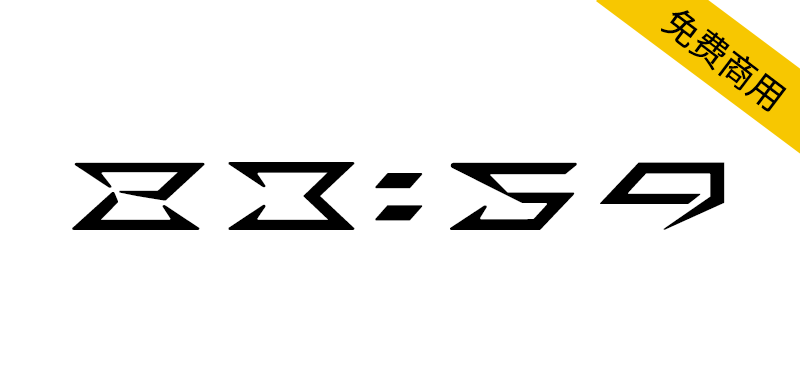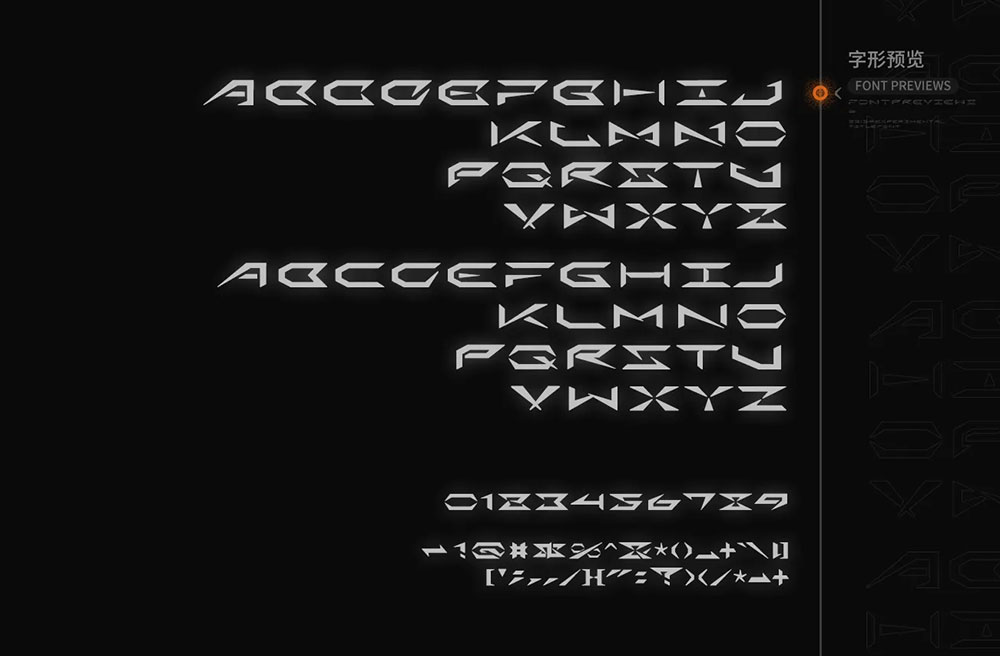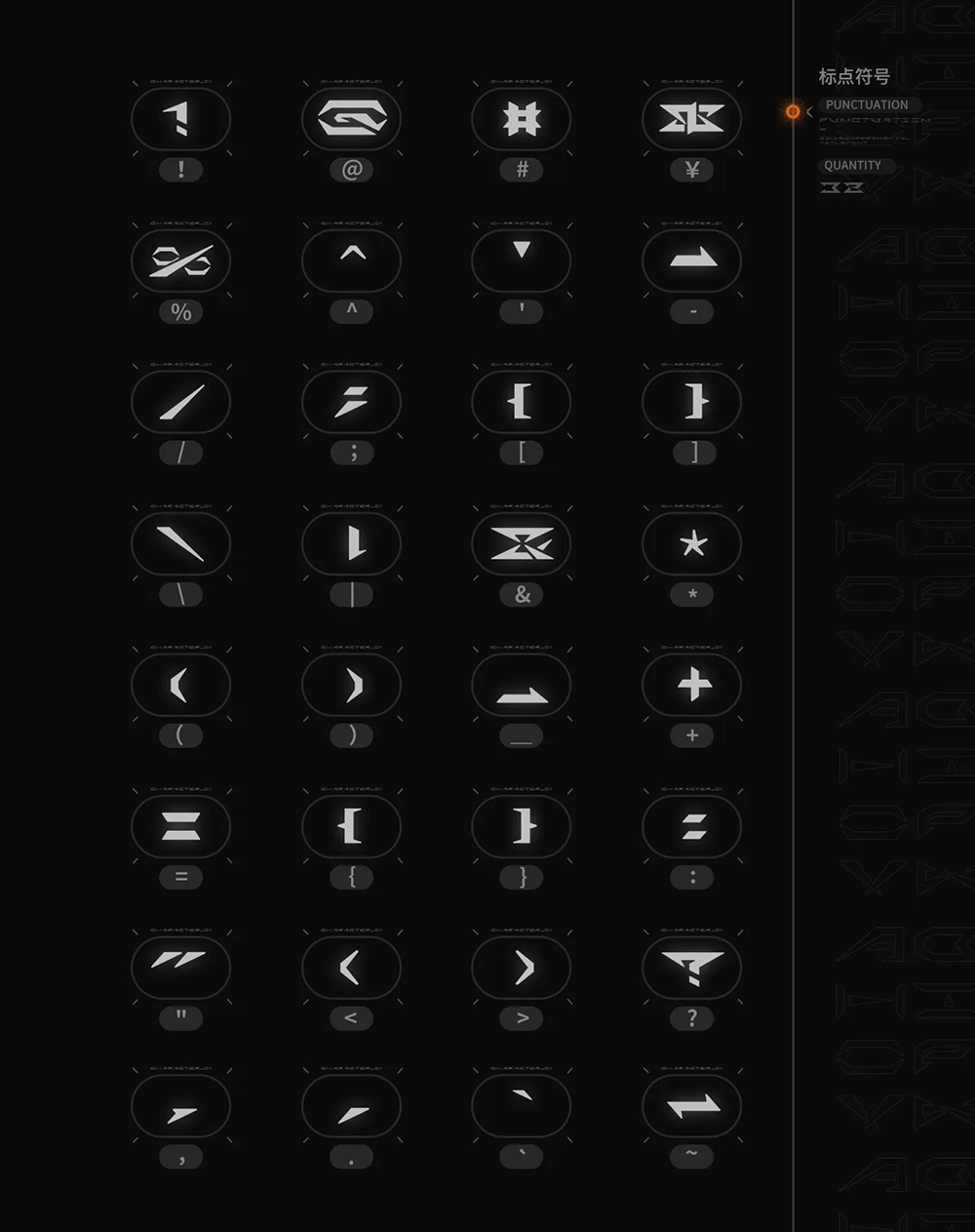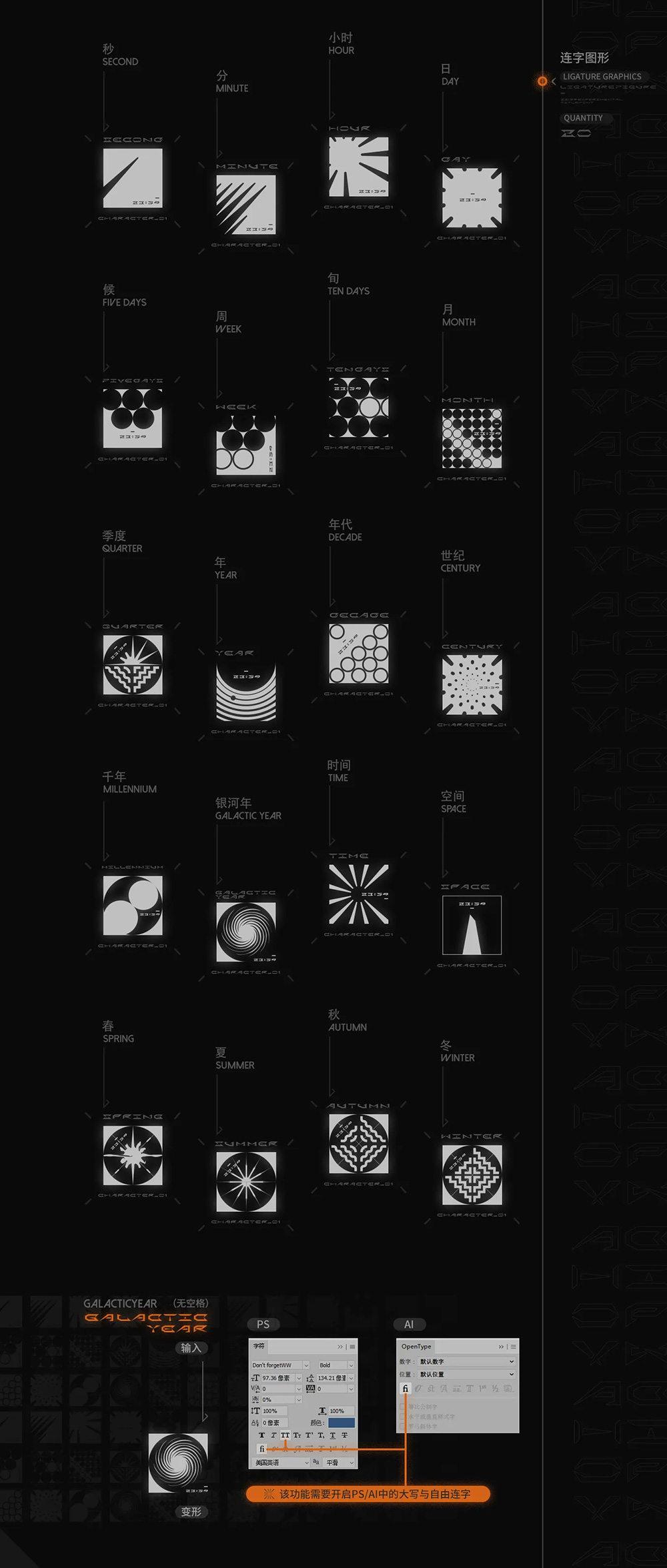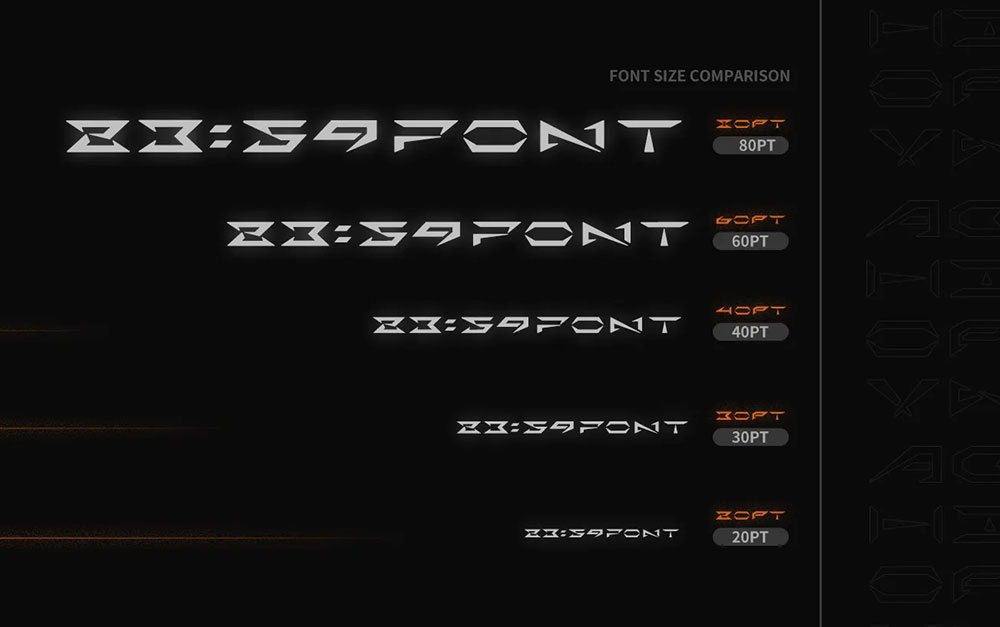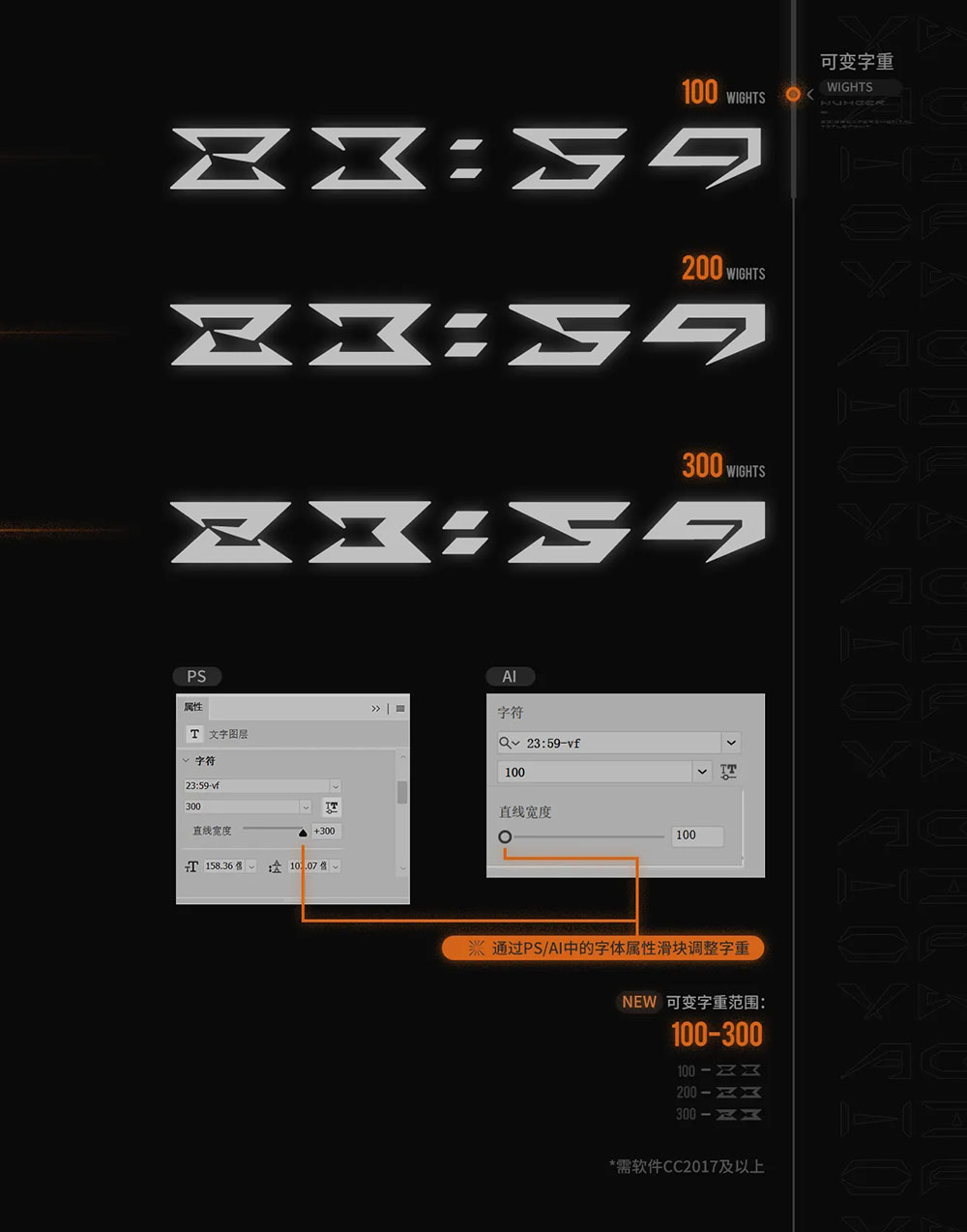
《23:59-贰拾叁点伍拾玖》是我基于对“时间”的思考和英语创作的免费开源实验性装饰字体。增加了可变字重功能,您可以在100-300字重范围当中随意选择,方便适用于各种应用场景。字体包含26个大写字母、26个小写字母(基于大写字母的简化)、42个标点符号和20个连字图形。
《23:59-贰拾叁点伍拾玖》是一款免费开源实验性装饰字体,不推荐您应用在正文排版设计当中。推荐应用场景:风格化标题、版面装饰、纹理装饰等。
《23:59-贰拾叁点伍拾玖》的设计源来自沙漏与指针,我保留了指针的指向性的同时,并使字形的字面更偏沙漏宽窄对比强烈的造型。我舍去了文字的部分辨识度,使其更加符号化。字形主要由直线和锐角构成,锐角上我增加了圆角处理,削弱了攻击感,增强了包容性。尖锐、硬朗、跳跃、神秘是《23:59》的主要气质,它非常适合应用在科幻、现代感、未来感、潮流感的影视、游戏视觉设计当中。
“时间”串联了过去、现在和未来,人们对自己人生各个阶段的时间感知都不同,所发生的事和所遇到的人也会引发各种不同的情感与感受。随着时间的推移,我逐渐开始怀念从前世间万物对我产生的影响,总是会回忆起那个夏天带给我的心潮澎湃,我也开始在寻找当初的各种感受,而回忆总有一天会被遗忘,因此我希望能够用设计的形式来纪念我还想寻找而寻找不到的感受。
“23:59”是一天中的最后一分钟,一分钟后一天将会被重置,我想用《23:59》传达出“时间”对人们产生的各种情感和意义,激发出人们对“时间”的思考与建立联系。作品的整个包装是一个竖向时间轴,连字图形是按照部分时间单位来进行设计,分别是秒、分、小时、日、候、周、旬、月、季度、年、年代、世纪、千年、银河年,以及四季中的春、夏、秋、冬、时间、空间。四季的转换对时间流动的感受最为强烈,不同季节中的体感影响了人们的情感状态,值得我们去思考与探索内心深处的感受。